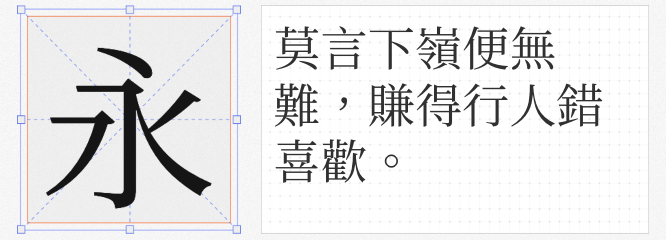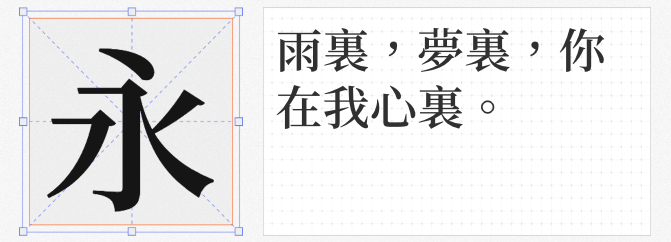
在香港这座东西文化交融的都市,繁体字体设计既承载着传统汉字美学,又需满足现代商业传播的严苛要求。本次精选四款兼具文化底蕴与实用价值的免费商用字体,它们或刚劲挺拔,或温润婉约,为港式视觉设计提供多元解决方案。
1.梦源黑体HK W14
作为思源可变字体的精细化演绎,该字体将数字时代的弹性美学转化为经典单字重呈现。层次丰富的字重体系覆盖从纤细到浑厚的完整梯度,在保持思源家族优异兼容性的同时,通过轮廓优化实现纸质印刷级的细节呈现。特别适合需要多层级信息排布的金融报表或品牌手册设计,让数字文件在跨平台输出时依然保持专业质感。
2.梦源宋体HK W14
延续思源字系的开放基因,这款宋体对香港用字习惯进行深度适配。在保留传统宋体"横细竖粗"韵律的基础上,通过轮廓合并技术消除低分辨率下的锯齿现象。23级字重选择既满足政府文书的庄重需求,又为文创产品提供轻盈的版式可能,堪称传统书卷气与现代功能性的平衡典范。
3.免费香港楷书
这款凝聚银发智慧的字体,承载着跨代际的文化传承使命。以教育局《常用字字形表》为基准,结合台湾正楷的骨架优化,在保持教育规范性的同时注入手写温度。特别适合教科书排版或儿童读物设计,圆润的起笔与适度的连笔处理,让汉字学习变得亲切生动。
4.思源宋体HK Regular
Adobe泛CJK字系的香港定制版本,在保持思源家族强大跨语言支持的同时,针对繁体字结构进行专项优化。这款字体在横排文档中展现出卓越的文本易读性,尤其适合需要中日韩三语兼容的包装设计或网页界面。其开放版权属性更使其成为跨国企业本地化设计的首选方案。
从金融街区的霓虹灯牌到旺角街头的文创小店,这四款字体构建起完整的香港设计语言体系。无论是追求现代极简的品牌视觉,还是传递文化温度的教育项目,都能在免费商用的框架下找到理想解决方案。当传统书法智慧遇见数字时代需求,这些带着东方韵味的字符,正在书写属于香港的设计新篇章。